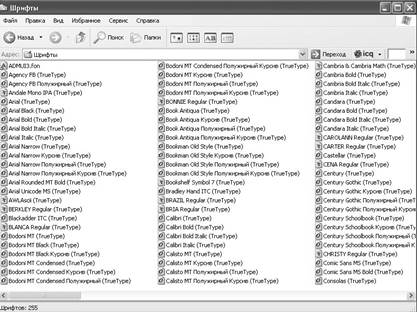
Шрифты с засечками (антиквенные)
При работе в графическом режиме каждый текстовый символ прорисовывается на экране монитора попиксельно, т. е. по точкам. По технологии «внутреннего строения» компьютерные шрифты делятся на три типа: растровые (bitmap-шрифты), векторные и контурные. Кроме того, шрифты условно делят на следующие стили(таблица 6.1) Таблица 6.1.
Ниже приведены образцы различных стилей шрифтов: Международный гуманитарный университет Windows XP хранит шрифты в специальной папке с названием Fonts (Шрифты). Стандартным путем к папке Fonts является С:\Windows\Fonts. Папка Шрифты содержит элемент для каждого установленного шрифта и используется Windows и ее приложениями. Открыть окно папки Шрифты для того, чтобы увидеть ее содержимое, можно с помощью программы Проводник. Можно открыть папку Шрифты с помощью Панели управления. После того как появится окно Панели управления, дважды щелкните на значке Шрифты для того, чтобы появилось окно Шрифты (рис. 6.3). Папка Шрифты – это стандартное окно папки с некоторыми отличиями.
На первый взгляд папка Шрифты кажется похожей на окно обычной папки, в которой содержится много значков различных шрифтов, установленных в системе. Подпись под каждым значком – название шрифта. Символы на значках в папке Шрифты показывают, к какому типу шрифтов он относится.Не все шрифты, установленные в Windows, должны сохраняться в папке Fonts. Для того чтобы Windows могла получить доступ к этим шрифтам, необходимо, чтобы в папке Шрифты находился значок шрифта, а не только сам файл шрифта. Вместо этого в папке Шрифты может находиться просто ярлык, который указывает на то, что файл шрифта сохранен в другом месте. Если открыть файл шрифта (рис. 6.4), можно получить информацию о шрифте и просмотреть его отображение. По умолчанию папка Шрифты содержит значки. Однако можно изменить способ отображения значков. Кнопки на стандартной панели инструментов папки Шрифты позволят выбрать четыре различных способа отображения папок.